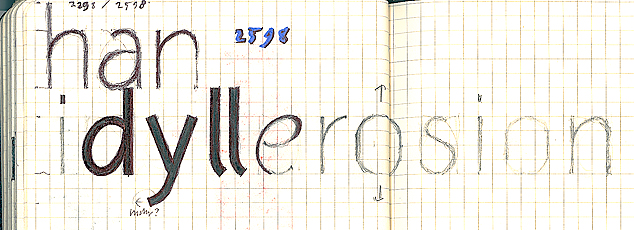
Entwicklung im Type Design
ich wollte dieses Thema schon vor einiger Zeit starten, weil ich mich immer wieder gerne mit dem Thema Schrift auseinandersetze.
In den letzten Jahren sind sehr viele serifenlose Linear-Antiqua Schriften auf den Markt gekommen, die inhaltlich an die Ideale der Renaissance-Schriften anknüpfen – offene und dynamische Formen (Meta, Fago, TheSans, Fedra Sans und zig hundert andere.).
Auch Antiqua-Schriften, wurden und werden vielfach offen und dynamisch gezeichnet – also ebenfalls der Renaissance-Art verpflichtet, meist moderner interpretiert.
Klar sind auch viele weitere Schriften erschienen die gar nicht in diese Ecke gehören, weil es sich dabei eher um grafische oder konstruierte Schriften handelt, aber die lasse ich mal schön beiseite.
Aber alles in allem, ist eine überwiegende Mehrheit an Schriften erschienen, die einen Bezug zur Renaissance aufweisen – nicht immer ausgeprägt aber doch klar erkennbar.
Aufgrund der besseren Lesbarkeit von dynamischen, offen gestalteten Schriften absolut nachzuvollziehen. :!:
Und trotzdem – in welche Richtung entwickelt sich das Type Design grundsätzlich? Was denkt Ihr? Ist ein neuer Trend erkennbar, oder bleibt alles beim Alten. Was für Schriften fehlen, wenn überhaupt welche fehlen. Welche Art von Schriften hättet Ihr gerne, die es Eurer Meinung noch nicht gibt? Wohin geht die Reise? :?
Derzeit ist der Trend wohl:
1. Hybrid-Formen die keiner der drei "Richtungen" exakt folgen.
2. Ausbau der Fähigkeiten, sprich: Sonderzeichen, Spezialverhalten, ... Alles was mit einem simplen Setzkasten kaum möglich war. Die erste Digitalisierungswelle, die benötigt wurde um den alten Bestand ins neue Format zu retten, ist vorbei, jetzt ist Zeit für "mehr".
Mein Berufsschullehrer sagte ca. 1985 zu uns, dass in der Renaissance die wohl schönsten Schriften überhaupt entstanden seien. Dem möchte ich mich anschließen und hinzufügen, dass die Renaissance seinerzeit ja ebenfalls eine Rückbesinnung auf Ideale und Vorstellungen der Antike gewesen ist.
Die inflationäre Entwicklung von Sans-Serif-Schriften macht mir eher Ärger. Jeder, der heute im 3. Semester Grafikdesign studiert, scheint ja seine eigene Sans Serif entwickeln zu wollen. Das halte ich für verfehlt.
Ansonsten läuft die Entwicklung im Schriftenmarkt derzeit sehr heterogen und unüberschaubar, finde ich. Es gibt hunderte kleiner »Labels« und ein paar größere, aber mit der Situation vor der Digitalisierung bzw. vor dem Fotosatz lässt sich das alles nicht mehr vergleichen. Linotype? Kaputt. Monotype? Wie viele Leute haben die eigentlich? Und sonst? Ist Fontshop jetzt Weltmarktführer oder wie? Was ist aus einer Firma wie z.B. Scangraphic geworden, die einst bei der Bild-Text-Integration die Nase richtig vorn hatten? Mir macht das alles keinen wirklichen Spaß mehr.
Ich finde, es geht gerade wieder viel in Richtung Barock (auch allgemein bei der Gestaltung z.B. Ornament-, Illustrations-, Bantjes-Welle) man könnte auch sagen Transitional, bzw. Übergangsantiqua, also wie Sebastian schon schrieb - nicht ganz Renaissance, aber auch nicht echt statisch.
Bei den Serifenlosen gibt's ebenfalls viele Schriften, die an die ursprünglichen und amerikanischen Grotesken angelehnt sind. So viele reinrassige Renaissance-inspirierte kommen mir gerade gar nicht in den Sinn aus der letzten Zeit.
das wenigste was ich in der gestaltung brauche sind trends.
schriften suche ich passend zum medium/design ich will da keine trends sehen.
vorallem nicht solche gewollten ichmussunbedingteineaußergewöhnlichesanswerdentrends.
Genau das nehmen sich aber einige beginnenden Gestalter wohl vor. Auch, weil wir immer sagen, man soll nicht das kopieren, was die anderen schon veröffentlicht haben. Also machen sie was originelles, vermischtes, gesampeltes.
Das trifft aber sicher nicht auf alle zu (siehe die neuen ourtypes z.B.)
können sie auch gern machen, gegen ourtype z.b. habe ich auch nix.
aber es gibt so formen da denke ich: "ohh gott, warum"? meistens
erwischt es dann ein paar buchstaben im ganzen font der ohne diese
"speziellen zeichen" jedoch ganz gut aussehe. man kann ihn dann nicht
als textfont einsetzten weil er zu eigenwillig ist allerdings auch nicht als
headlinefont weil die idee nicht durchgezogen wurde. er würde sich gerade
noch als logofont verwenden wenn man denn mal ein ausgefallenes
zeichen sucht. problem hierbei: es kann jeder verwenden.
nichts gegen die ersten versuche von typedesign-studenten ...
ich muss es ja nicht kaufen, wann wird nur in letzter zeit damit überschüttet.
vielleicht sehe ich das aber auch etwas zu überspitzt.
Es ist heute halt sehr einfach, eine Schrift zu veröffentlichen. Und hip.
Wegen mir kann jeder mit solchen »Konzept-Schriften«, wo alle Zeichen einem »Programm« unterworfen werden, seinen Einstieg, bzw. sein Interesse für Schriftgestaltung finden. Vielleicht lernt er dabei auch die traditionellen Schriften zu würdigen. Aber warum muss man das alles in die Welt setzen?
Aber sie sind auch so schön, weil sie genau auf Text, Platz, Aufgabenstellung, Zielgruppe abgestimmt sind. Die Gestalter und Buchstaben sind frei und müssen nur mit den jeweiligen Nachbarn können (oder auch nicht), nix kerning, hinting, juppheidi, man könnte sich also das ganze doofe an der Schriftgestaltung sparen. Für die ohne Stifte und Pinsel geht das natürlich auch digital, so wie früher Kopieren und Kleben.